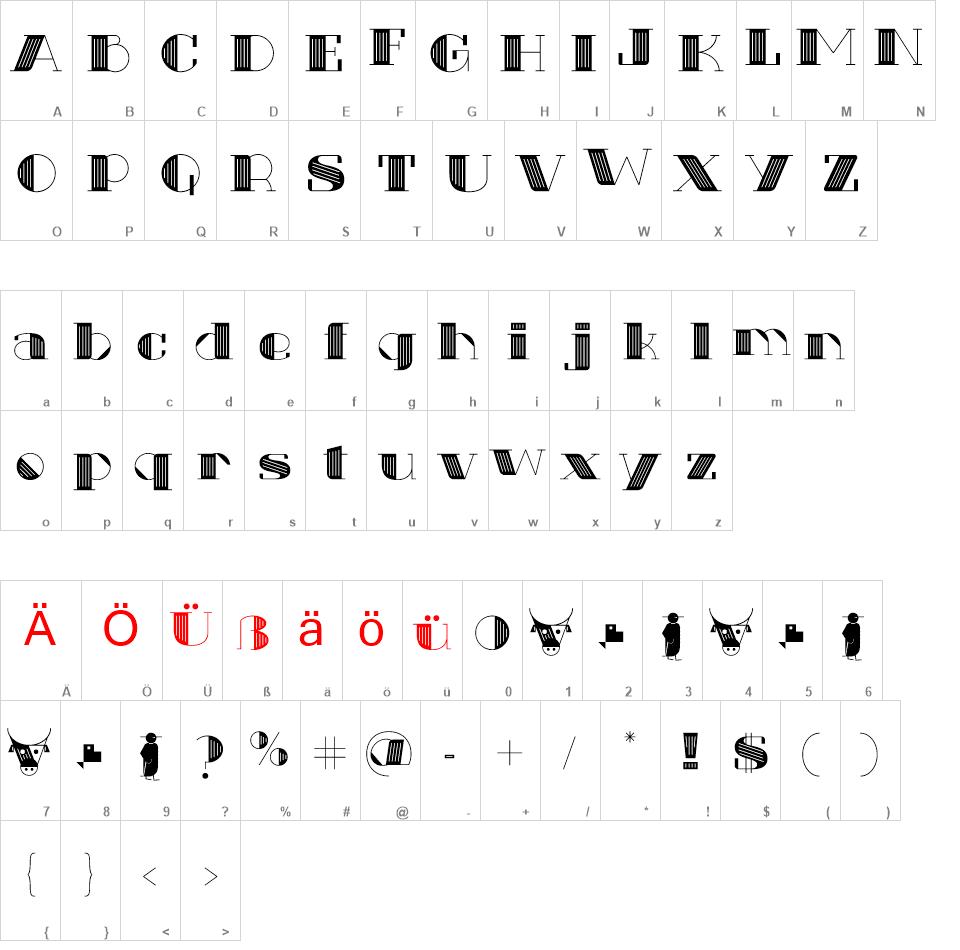
Txuleta Deco
Txuleta Deco Txuleta ist eine elegante Display-Art des modernistischen Stils, der geometrischen Konstruktion und des breiten Anteils. Txuleta ist ein modernisierter Nachkomme der Didonas-Typographien, mit extremem Gegensatz zwischen Geweih und dünnen Bodoni-Serifen. Die Typografie besteht aus 3 kombinierbaren Stilen für Layer, um mehrfarbige typografische Überschriften zu erzeugen. Txuleta enthält alternative Buchstaben für Groß- und Kleinbuchstaben, alte Stilnummern und andere Open Type-Funktionen. ========================== VOLLVERSIONEN UND KOMMERZIELLE LIZENZ: defharo.com/fonts/txuleta-display/ rrr